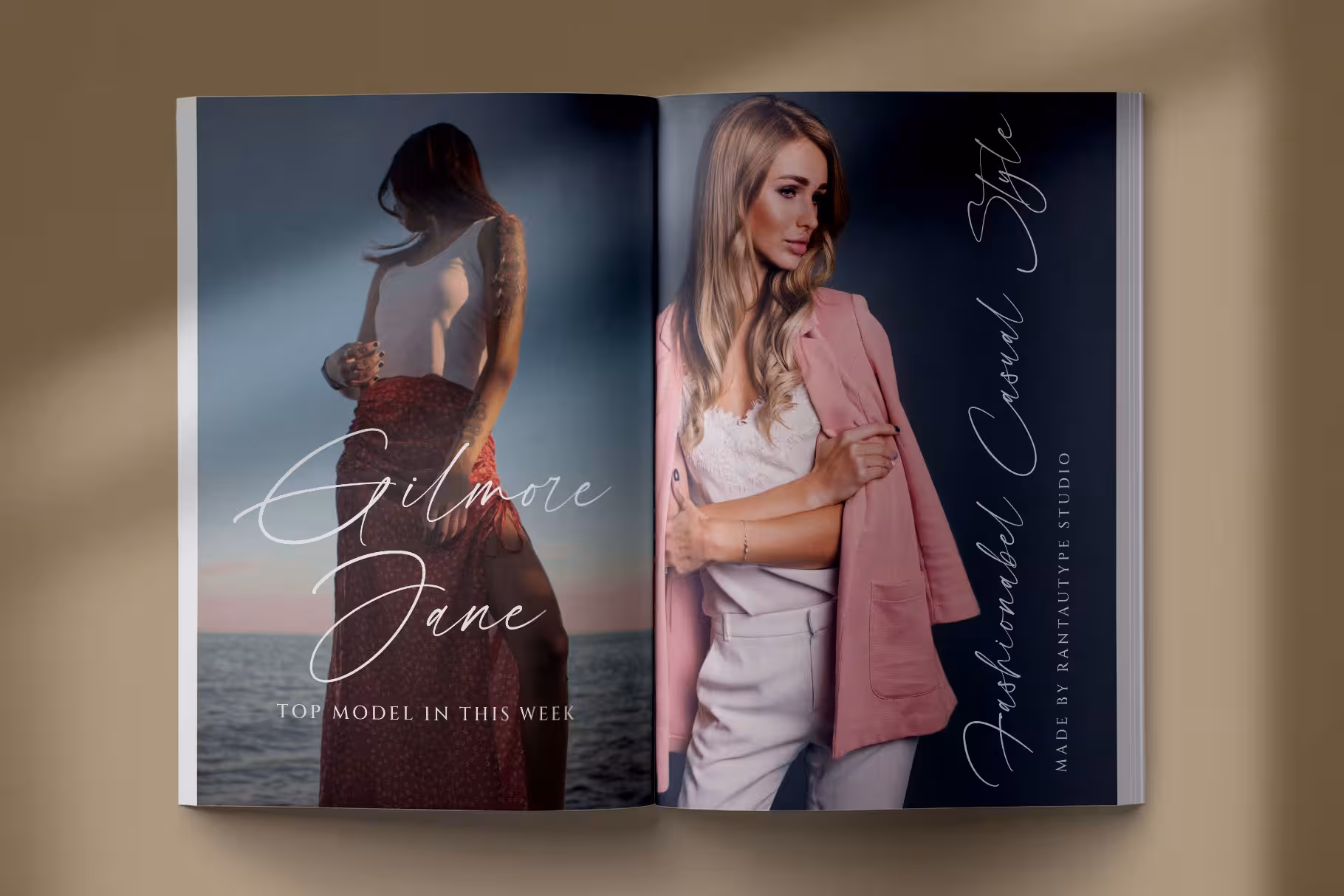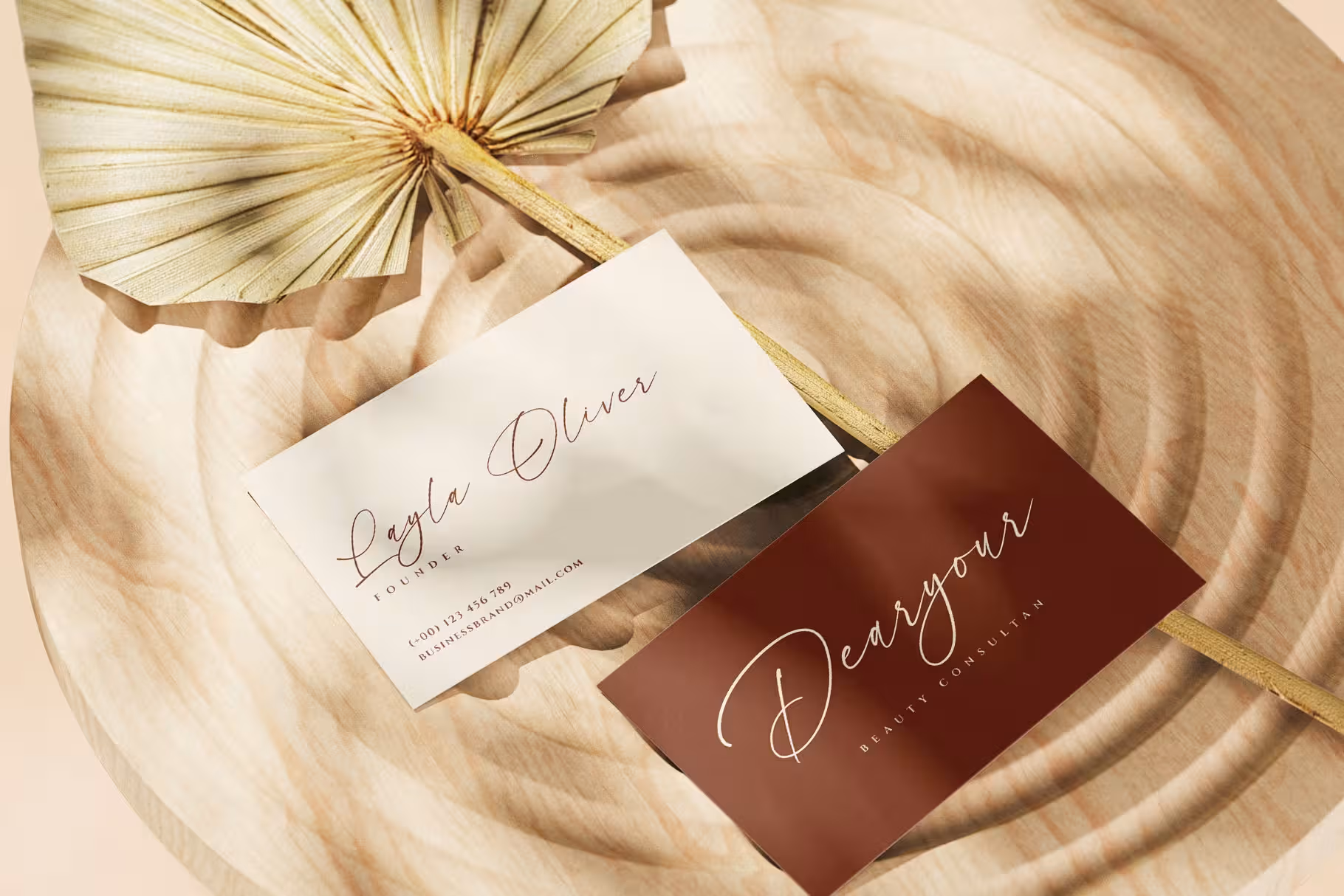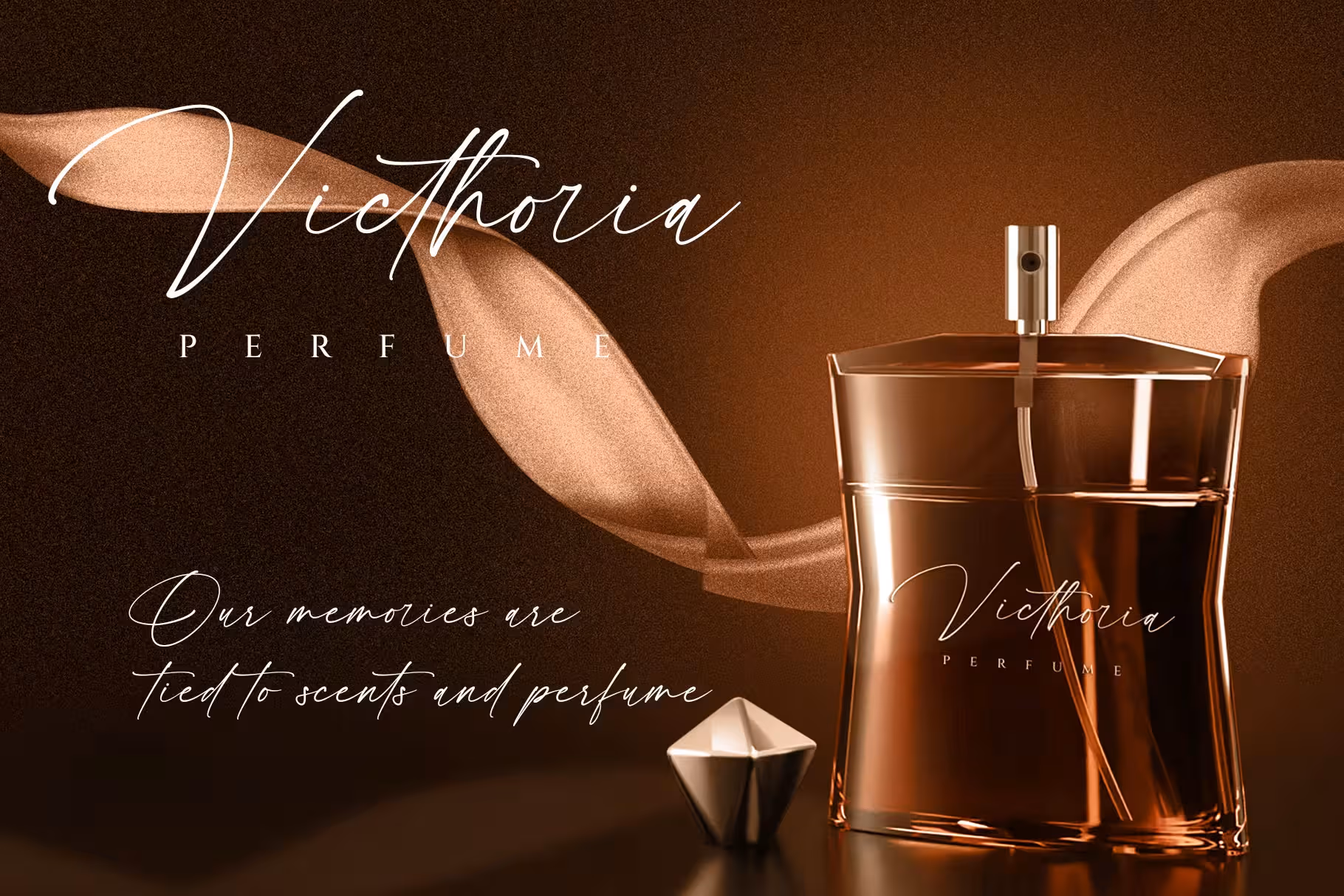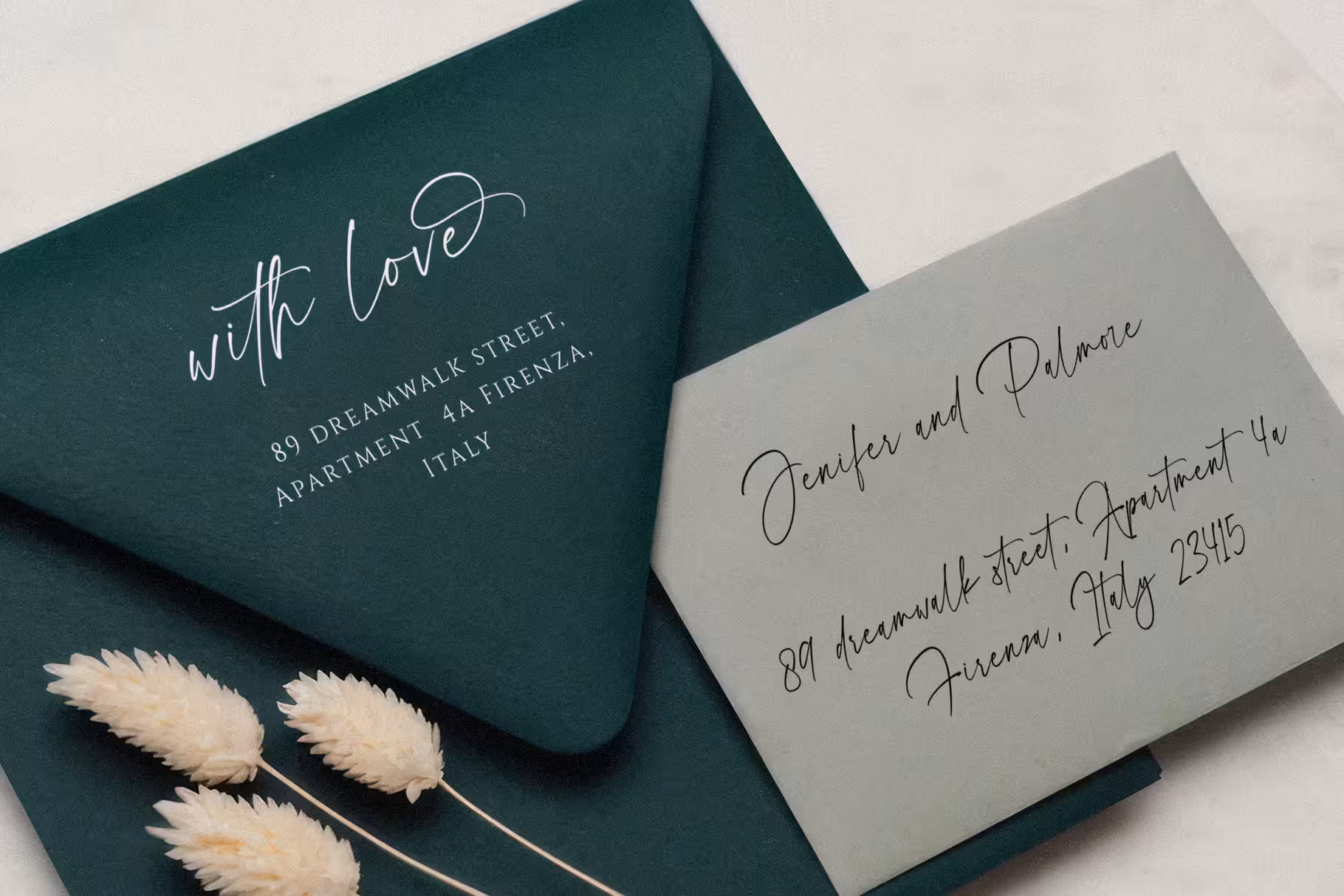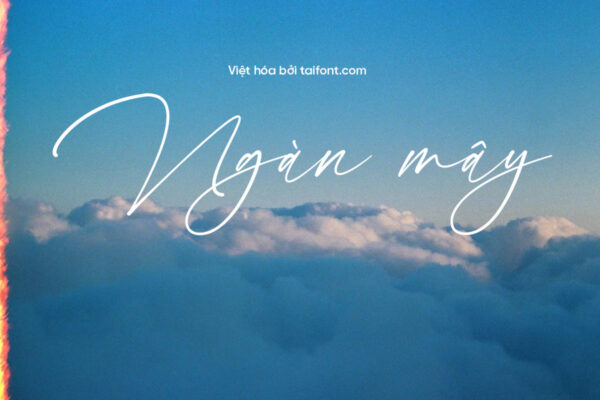
Giới thiệu về Font TF Hastheya Việt hóa
TF Hastheya Việt hóa là một font chữ viết tay (script font) nổi bật với vẻ đẹp tinh tế, độc đáo và đầy thú vị, mang đến phong thái nghệ thuật và cá tính. Font này gợi cảm giác như những nét chữ ký được viết tay một cách tự nhiên, phóng khoáng nhưng vẫn giữ được sự duyên dáng, lý tưởng để tạo điểm nhấn riêng biệt và thu hút mọi ánh nhìn.
Với sự duyên dáng trong từng đường nét và tính thẩm mỹ cao, Hastheya là lựa chọn hoàn hảo cho các thiết kế muốn truyền tải sự tinh tế, cá nhân hóa và một chút nghệ thuật:
- Thiết kế name card: Hoàn hảo để sử dụng trên danh thiếp, đặc biệt cho các ngành nghề liên quan đến nghệ thuật, sáng tạo, hoặc các cá nhân muốn tạo ấn tượng độc đáo và cá tính. Font này giúp name card trở nên chuyên nghiệp, nhưng vẫn mang đậm dấu ấn riêng và dễ nhớ.
- Thiết kế thời trang: Lý tưởng cho các thương hiệu thời trang muốn truyền tải sự tinh tế, độc đáo và một chút phong cách thủ công. Hastheya có thể dùng cho logo, nhãn mác sản phẩm, lookbook, hoặc các chiến dịch quảng bá bộ sưu tập, nâng tầm giá trị cảm nhận của sản phẩm.
- Thiết kế nước hoa: Phù hợp để sử dụng trên bao bì sản phẩm, nhãn chai, hoặc các chiến dịch quảng bá nước hoa. Font này giúp khẳng định chất lượng, sự sang trọng và vẻ đẹp tinh túy của sản phẩm, thu hút ánh nhìn của khách hàng và truyền tải thông điệp về sự quyến rũ, đẳng cấp một cách cá tính.
- Trích dẫn và slogan: Tuyệt vời để tạo các câu trích dẫn đầy cảm hứng, slogan hoặc các dòng chữ cần sự nổi bật và mang tính biểu cảm trên mạng xã hội hoặc các ấn phẩm khác.
Với TF Hastheya Việt hóa, bạn có thể dễ dàng thổi hồn nghệ thuật, sự tinh tế và cá tính vào các thiết kế, tạo ra những sản phẩm không chỉ đẹp mắt mà còn đầy cảm xúc và sức hút đặc biệt.